Tipografía Legible: Clave del Diseño Web Efectivo
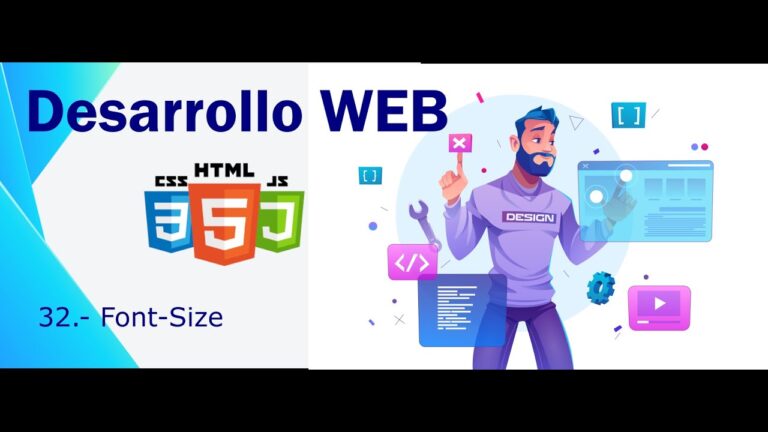
La tipografía legible es un elemento esencial en el diseño web, ya que influye directamente en la experiencia del usuario y en la efectividad de la comunicación visual. Elegir fuentes que sean fáciles de leer no solo mejora la accesibilidad, sino que también refuerza la identidad de la marca. En un mundo digital saturado de información, la claridad tipográfica se convierte en un factor clave para captar y mantener la atención del público. A continuación, examinaremos cómo una tipografía adecuada puede transformar la percepción y funcionalidad de un sitio web.
¿Qué hace a la tipografía legible esencial?
La tipografía legible es esencial en el diseño web porque facilita la lectura, mejora la experiencia del usuario y transmite el mensaje de manera clara.
¿Qué se entiende por tipografías legibles?
La legibilidad tipográfica se refiere a la facilidad con la que se puede percibir y entender un texto, un aspecto fundamental en el diseño gráfico y la comunicación escrita. Tipografías bien diseñadas permiten que el lector se desplace por el contenido sin esfuerzo, mejorando la experiencia de lectura y asegurando que el mensaje se transmita de manera competente. Por el contrario, algunas tipografías pueden dificultar la lectura, lo que puede ser intencional en ciertos contextos artísticos o publicitarios.
La elección de una tipografía legible es clave, ya que influye directamente en la claridad y atractivo del contenido. Tipos de letra como Arial o Helvetica son ejemplos de fuentes ampliamente reconocidas por su legibilidad, mientras que otras, más decorativas o estilizadas, pueden resultar confusas y poco prácticas. En definitiva, la tipografía adecuada no solo embellece el texto, sino que también facilita su comprensión, haciendo que el mensaje llegue de manera clara y directa al público.
¿Cuál es la tipografía más adecuada para un sitio web?
La elección de la tipografía adecuada es fundamental para la estética y la legibilidad de una página web. Las fuentes sans serif, caracterizadas por la ausencia de remates en sus letras, ofrecen un aspecto contemporáneo que resuena bien con las tendencias actuales del diseño digital. Su simplicidad permite que los usuarios se concentren en el contenido sin distracciones innecesarias.
Además, las tipografías sans serif son altamente legibles en pantallas, lo que las convierte en una opción ideal para la navegación en línea. Esto es especialmente importante en un entorno donde los visitantes esperan una experiencia fluida y agradable. Al utilizar estas fuentes, se mejora la accesibilidad y se garantiza que el mensaje de la marca sea claro y directo.
Finalmente, optar por una fuente sans serif puede contribuir claramente a la identidad visual de un sitio web. Transmiten una sensación de modernidad y profesionalismo, lo que puede generar confianza en los usuarios. En un mundo digital donde la primera impresión cuenta, elegir la tipografía correcta es un paso esencial hacia el éxito en línea.
¿Qué significa tipografía en el diseño web?
La tipografía en diseño web es un elemento fundamental que abarca no solo la elección de la fuente, sino también aspectos como el tamaño, el color y el formato del texto. Una buena tipografía no solo mejora la estética de una página, sino que también facilita la lectura y la navegación del usuario, creando una experiencia más agradable y competente. Al seleccionar cuidadosamente estos elementos tipográficos, los diseñadores pueden transmitir la personalidad de la marca y guiar al visitante a través del contenido de manera clara y atractiva.
La Importancia de la Tipografía en la Experiencia del Usuario
La tipografía desempeña un papel clave en la experiencia del usuario, ya que influye directamente en la legibilidad y la percepción del contenido. Una selección adecuada de fuentes puede mejorar la comprensión del mensaje, facilitando la navegación y el disfrute del usuario. Al elegir tipografías que se alineen con la identidad de la marca y que sean visualmente atractivas, se puede captar la atención y crear una conexión emocional con el público, lo que a su vez fomenta la confianza y la fidelidad.
Además, la tipografía contribuye a la jerarquía visual y a la organización del contenido. Un uso efectivo de tamaños, estilos y colores permite guiar al usuario a través de la información de manera intuitiva. Esto no solo mejora la usabilidad, sino que también potencia la estética general del diseño. En un entorno digital donde la competencia es feroz, prestar atención a la tipografía puede marcar la diferencia entre una experiencia satisfactoria y una frustrante, asegurando que los usuarios regresen una y otra vez.
Cómo Elegir Fuentes que Atraen y Retienen
Elegir las fuentes adecuadas es fundamental para captar la atención de tu audiencia y mantener su interés. Opta por tipografías que sean legibles y que reflejen la personalidad de tu marca; una combinación de fuentes serif y sans-serif puede aportar un toque dinámico y atractivo. Además, considera el tamaño y el contraste, ya que una buena visibilidad facilita la lectura y refuerza el mensaje. No olvides la importancia de la coherencia; utilizar un mismo estilo de fuente en diferentes plataformas genera una identidad visual sólida y profesional, lo que a su vez fomenta la confianza y la conexión con tus lectores.
Estrategias para Mejorar la Legibilidad en tu Sitio Web
La legibilidad de un sitio web es fundamental para atraer y retener la atención de los usuarios. Para mejorarla, es esencial utilizar tipografías claras y tamaños de fuente adecuados que faciliten la lectura en diferentes dispositivos. Además, el contraste entre el texto y el fondo debe ser suficiente para que la información destaque sin causar fatiga visual. Incorporar espacios en blanco de manera estratégica también ayuda a que el contenido se vea más organizado y menos abrumador.
Otra estrategia competente es estructurar el contenido con encabezados y listas, lo que permite a los lectores escanear rápidamente la información. Utilizar un lenguaje sencillo y directo, evitando jergas innecesarias, también contribuye a que el mensaje sea accesible para un público más amplio. Por último, incluir imágenes y gráficos relevantes no solo hace que el contenido sea más atractivo, sino que también ayuda a ilustrar conceptos complejos de manera visual, mejorando así la comprensión general del material.
La tipografía legible se erige como un elemento esencial en el diseño web, ya que no solo mejora la experiencia del usuario, sino que también refuerza la identidad de la marca. Elegir las fuentes adecuadas y garantizar su claridad puede marcar la diferencia entre un sitio atractivo y uno que frustrante. Invertir en una tipografía bien pensada es, sin duda, un paso clave hacia un diseño web efectivo y profesional.